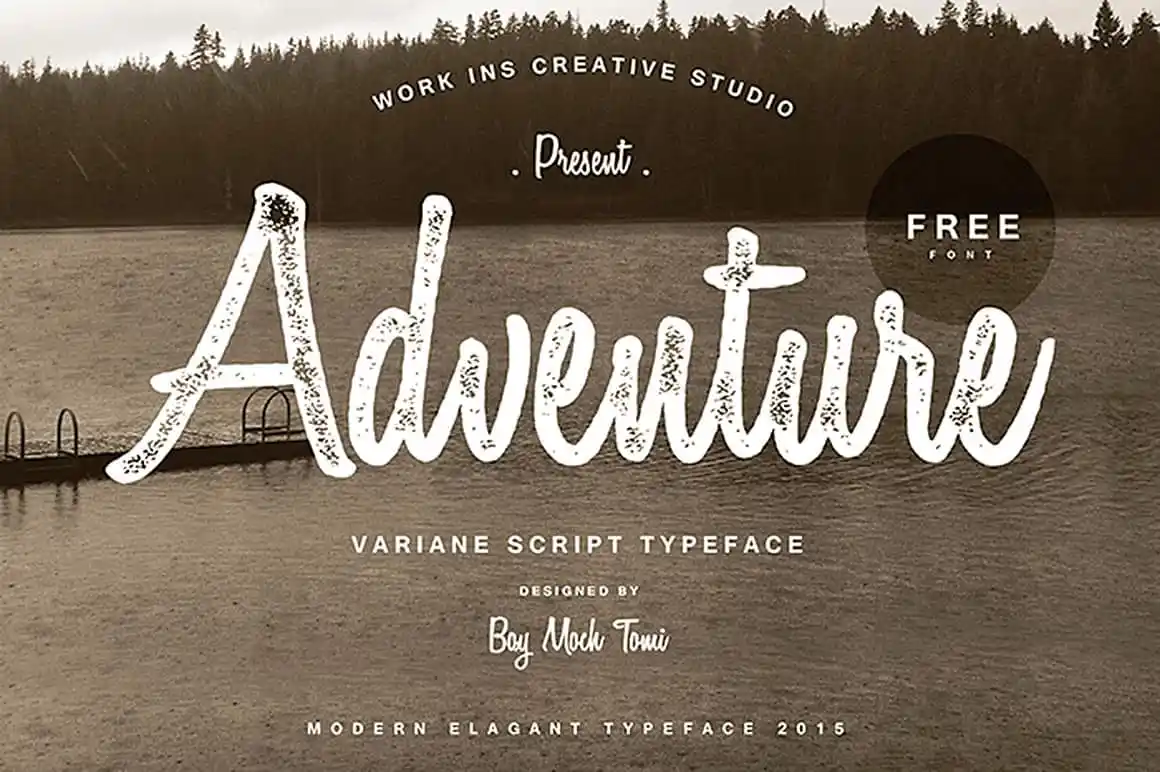
Variane Script Font – Download Grátis
Aqui está uma descrição curta e envolvente para a página de download da font ‘Variane Script Font’, criada pelo designer Hamilton: ‘Veraneia é uma elegante font customizada com traços script, perfeita para novas criações artísticas. Esta font foi originalmente lançada pela Boy Moch Tomi e agora está disponível para que você possa usá-la no seu próximo projeto gráfico. Descarregue-a hoje e desfrute dessa excelente opção para adicionar um toque de personalidade aos seus trabalhos.’